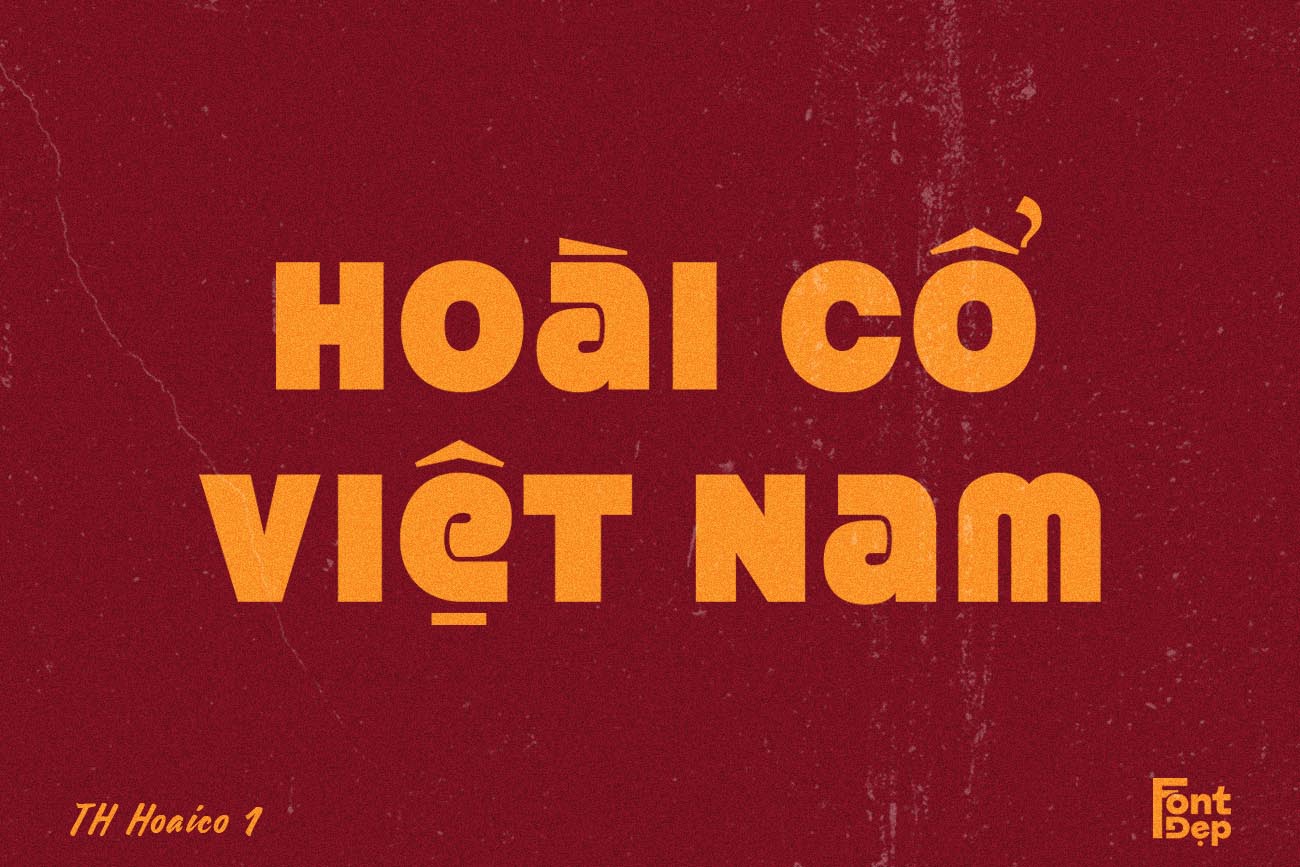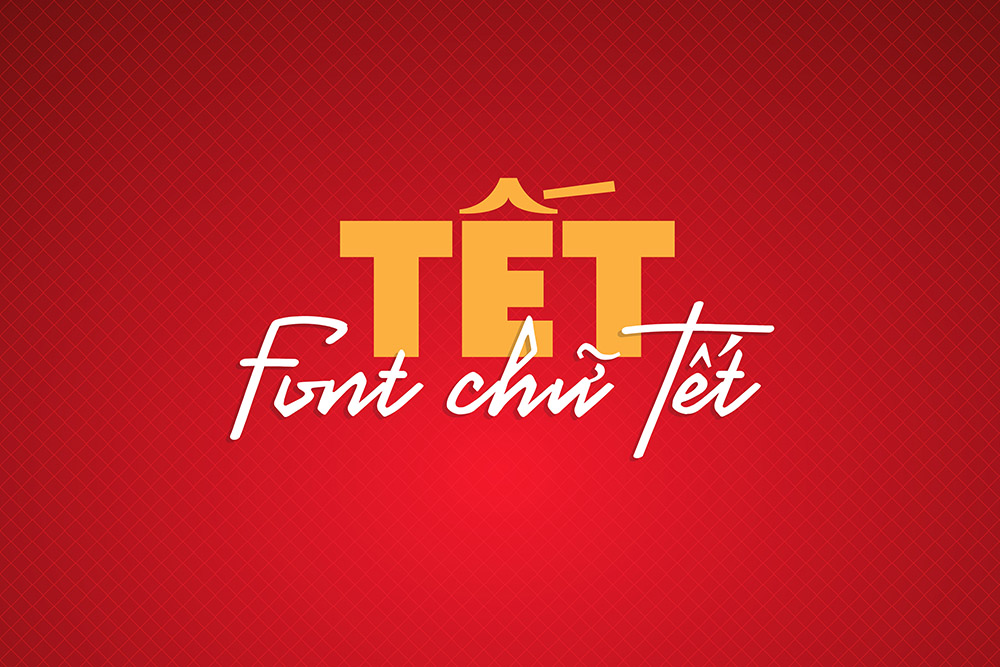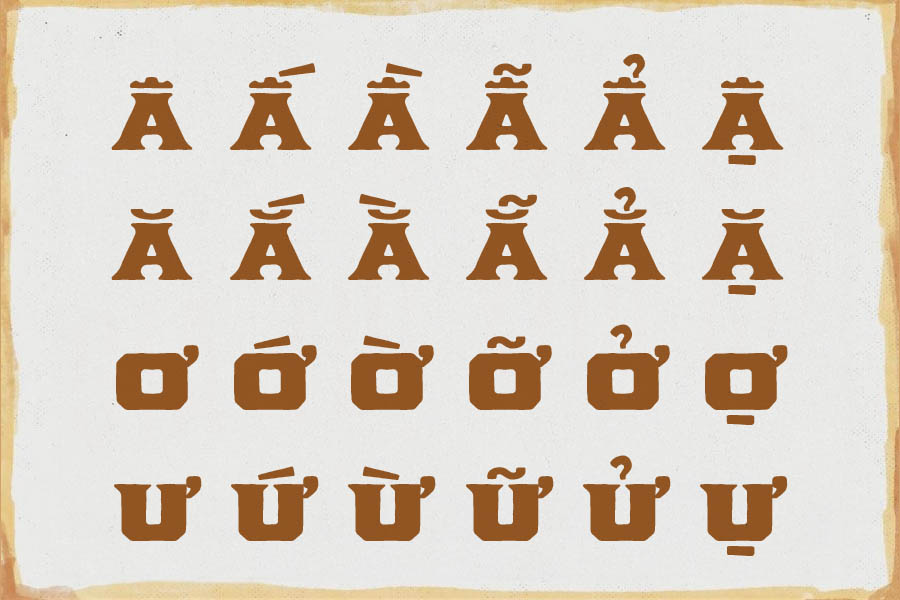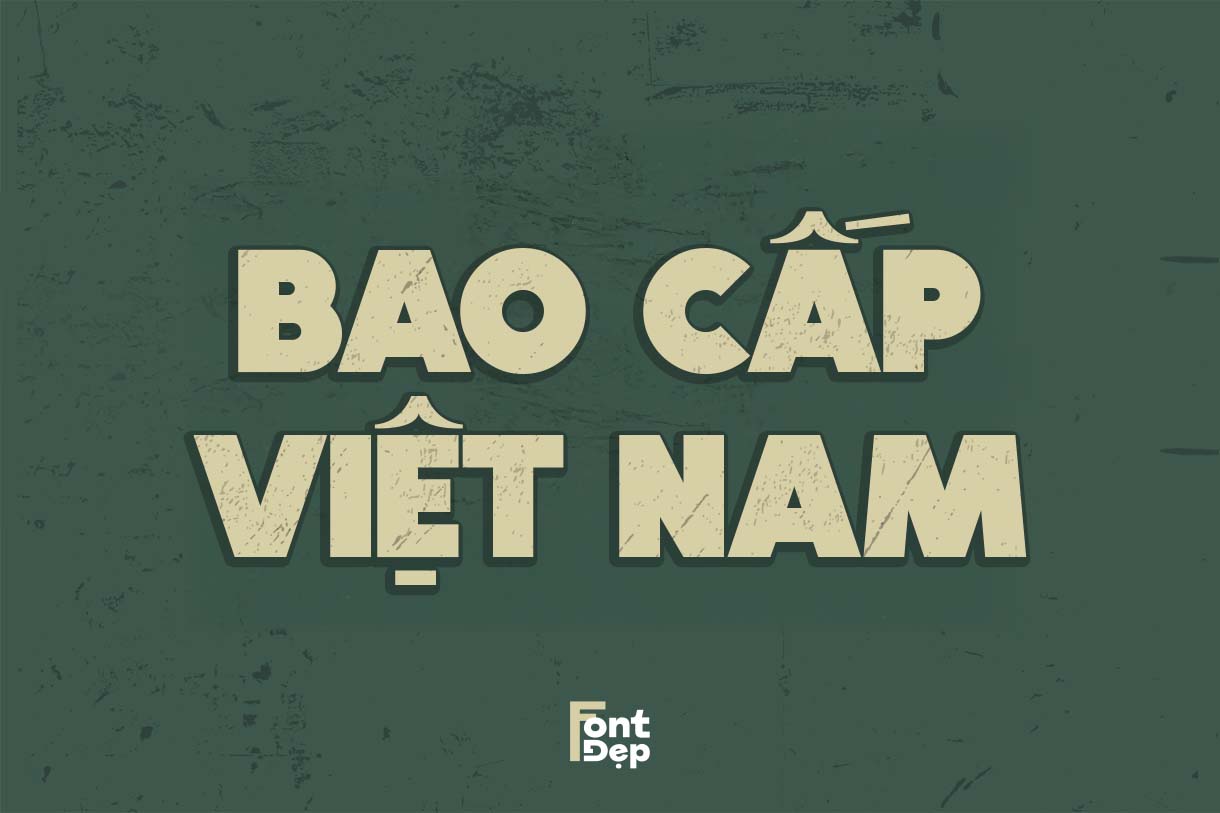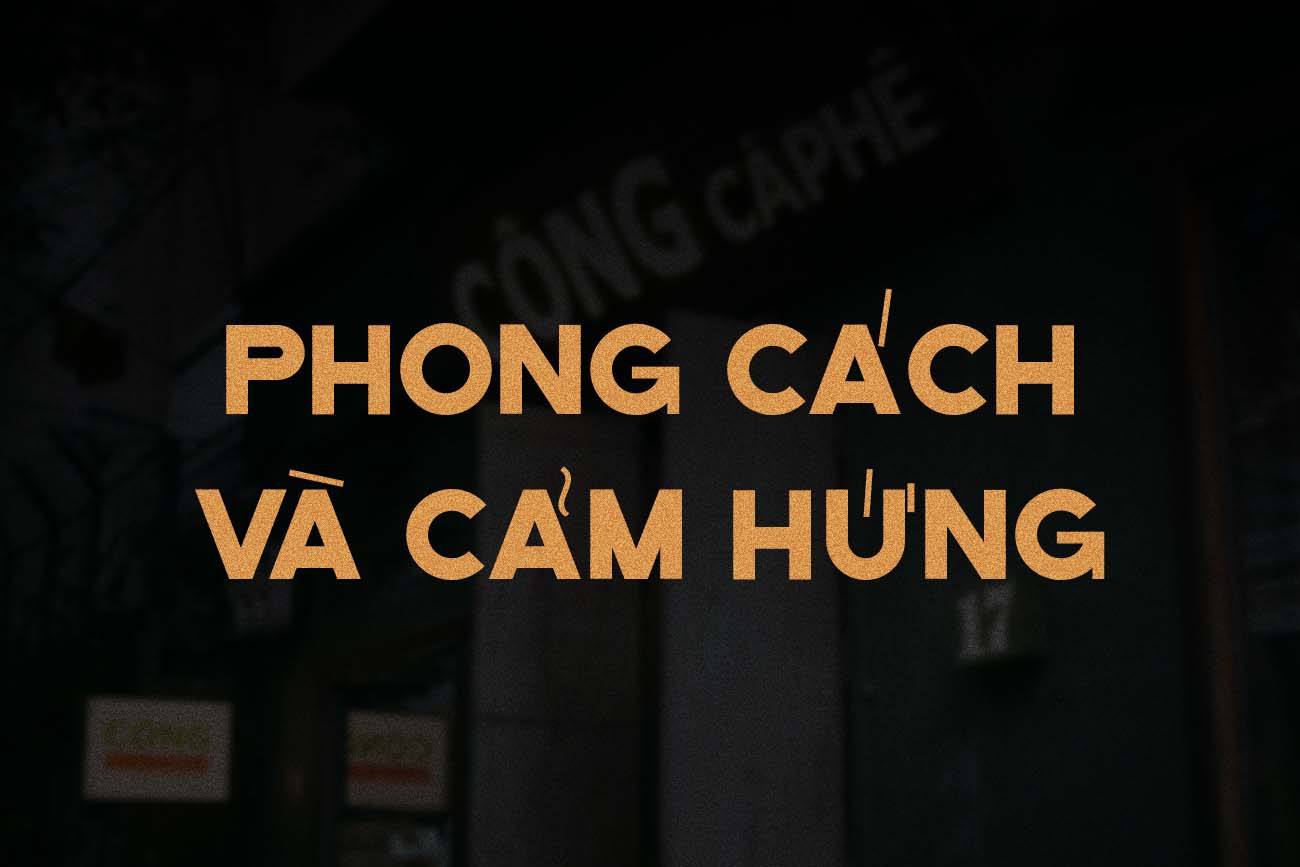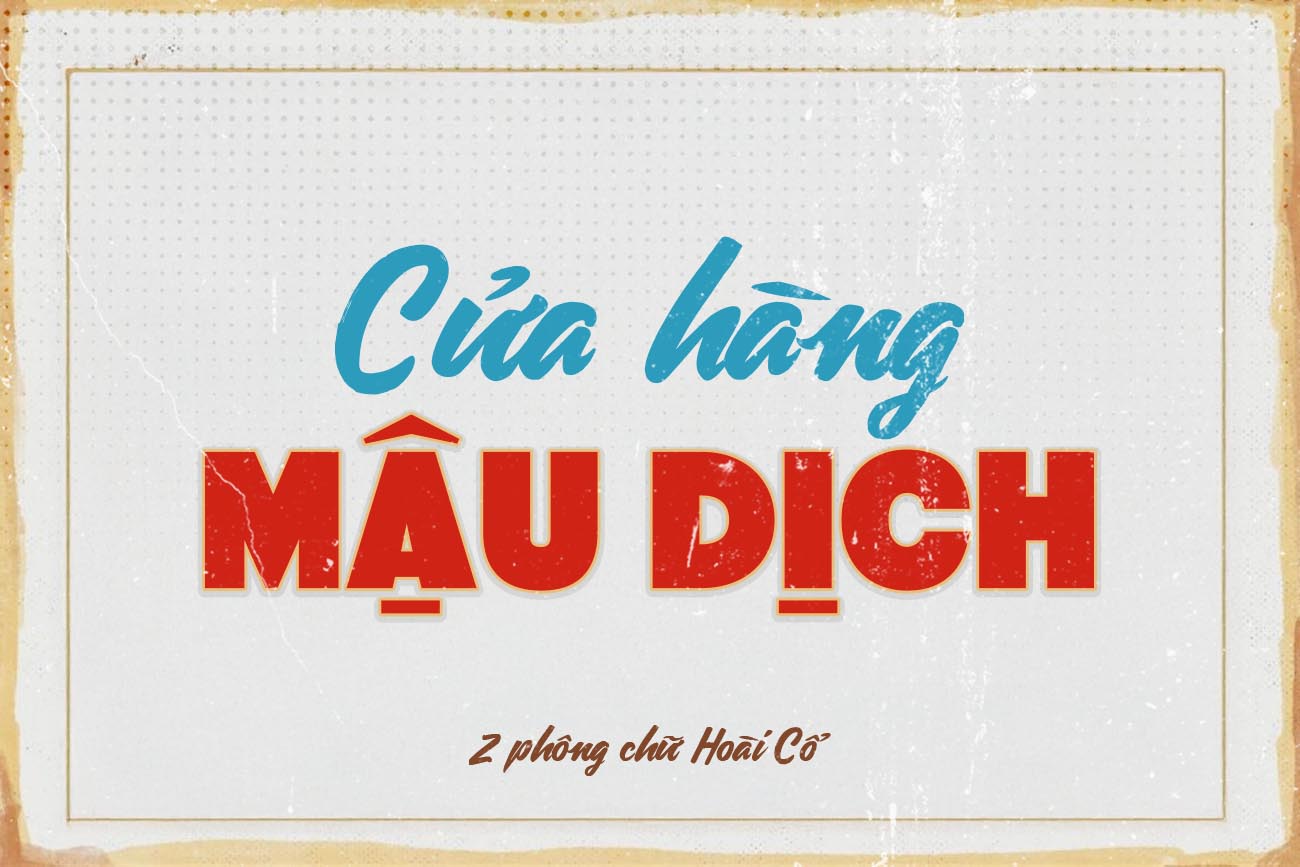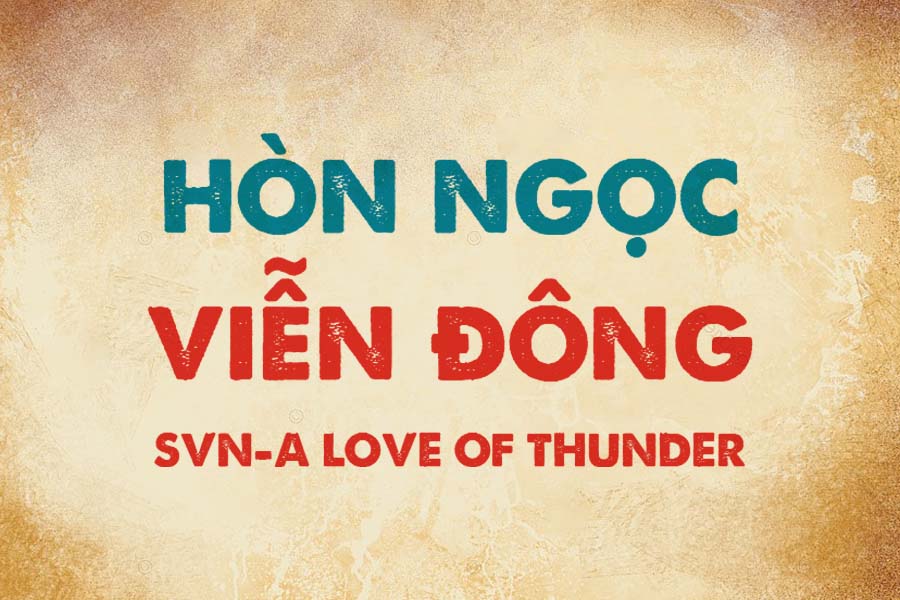
Bộ sưu tập Font Chữ Thời Bao Cấp Việt Hóa tái hiện trọn vẹn tinh thần hoài cổ Việt Nam, kết hợp di sản xưa với thẩm mỹ thiết kế hiện đại đầy cảm xúc.
Tải ngay Bộ Sưu Tập Font Chữ Thời Bao Cấp Việt Hóa – từ phong cách mộc mạc, thủ công đến nét viết tay bay bổng, tái hiện trọn vẹn cảm xúc hoài niệm và sâu lắng của những năm tháng cũ.
Bộ sưu tập hoàn hảo giúp bạn tạo nên những ấn phẩm thiết kế đậm chất xưa, giàu cảm xúc và chuyên nghiệp.
Font chữ thời Bao Cấp (khoảng thập niên 1970–1980) không chỉ là một kiểu chữ, mà là dấu ấn văn hóa – nhân chứng cho một giai đoạn đặc biệt của Việt Nam.
Việc sử dụng những font này giúp truyền tải sự chân thật, mộc mạc, thủ công – điều mà các font hiện đại khó có thể mô phỏng được.
Trong bài viết này, Fontdep.vn sẽ gợi ý những font chữ Bao Cấp / Hoài Cổ Việt Hóa chất lượng cao nhất, giúp bạn dễ dàng chọn được kiểu chữ hoàn hảo để hồi sinh nét đẹp hoài niệm trong mọi dự án thiết kế.
Font Chữ Thời Bao Cấp: Dấu Ấn Typography Của Một Giai Đoạn Lịch Sử
Font chữ thời Bao Cấp là gì?
Định nghĩa
Font Chữ Thời Bao Cấp là thuật ngữ chỉ các kiểu chữ được sử dụng rộng rãi trong các ấn phẩm, bảng hiệu, áp phích tuyên truyền, và bao bì sản phẩm trong thời kỳ kinh tế kế hoạch hóa tập trung (thời kỳ Bao cấp) tại Việt Nam.
Bối cảnh thiếu thốn vật liệu và công nghệ in ấn hiện đại đã buộc người thợ phải tự tay thiết kế và vẽ chữ, tạo nên một phong cách typography độc đáo: tự phát, thủ công, đầy ngẫu hứng và chân thật. Phong cách này khác biệt hoàn toàn với sự chuẩn mực của font kỹ thuật số ngày nay.
Đặc Điểm Nhận Dạng (Hình thái) Của Font Bao Cấp:
Các font mô phỏng phong cách Bao cấp thường mang những đặc trưng hình thái sau:
• Tính Thủ Công & Đơn Giản: Font thường là dạng Sans Serif hoặc Script thô sơ, mô phỏng nét cọ, nét sơn, thiếu sự đối xứng, hoàn hảo của font hiện đại.
• Tâm Lý Thiết Kế: Màu sắc, bố cục thường gắn với sự lạc quan, tuyên truyền và sự chắt chiu (tận dụng không gian).
• Yếu Tố Việt Hóa Quyết Định: Yếu tố quyết định là việc xử lý các dấu tiếng Việt (thanh sắc, huyền, hỏi, ngã, nặng) phải giữ được nét thủ công, không quá cứng nhắc, tránh phá vỡ sự liền mạch của chữ.
Ứng Dụng Nổi Bật Của Font Chữ Bao Cấp Trong Thiết Kế Hiện Đại
Font chữ thời Bao cấp có tính ứng dụng rất đa dạng, đặc biệt quan trọng trong các ấn phẩm cần truyền tải chiều sâu hoài niệm, sự mộc mạc thủ công và chất xưa độc đáo:
• Thương hiệu Ẩm thực Truyền thống: Sử dụng font Mộc mạc & Bảng hiệu cho bao bì cà phê rang xay thủ công, đặc sản địa phương, hoặc logo quán ăn/thương hiệu gợi nhớ hương vị xưa cũ.
• Thiết kế Hoài cổ/Retro Việt Nam: Áp dụng font Retro & Ấm áp cho poster phim, trang trí nội thất quán cà phê, hoặc các ấn phẩm tái hiện không khí thập niên 70-90.
• Ấn phẩm Cá nhân hóa/Nghệ thuật: Dùng font Viết tay & Bay bổng cho thiệp mời sự kiện cá nhân, chữ ký thương hiệu thời trang thủ công, hoặc tiêu đề blog mang tính kể chuyện.
• Sự kiện Văn hóa/Cộng đồng: Sử dụng font Mộc mạc/Script để thiết kế bảng chào mừng hoặc banner cho các lễ hội, sự kiện văn hóa cộng đồng cần sự chân thật và gần gũi.
Danh Sách 10 Font Chữ Thời Bao Cấp/Hoài Cổ Việt Hóa Tuyệt Đẹp
Fontdep.vn đã tuyển chọn 10 font chữ thời bao cấp tiêu biểu, được chọn lọc và Việt Hóa hoàn chỉnh, giúp nhà thiết kế dễ dàng áp dụng.
1. Font Sans-serif DT Phudu Việt Hóa – Mộc mạc, đồng quê
Font DT Phudu là font chữ cổ điển mang phong cách đồng quê Việt Nam, với những nét vẽ mộc mạc và hơi thô, mô phỏng chữ vẽ tay trên biển hiệu vùng quê. Font này đặc biệt phù hợp cho các dự án về văn hóa dân gian, nông nghiệp, làng nghề truyền thống, Tết Nguyên Đán.
Font chữ phong cách hoài cổ của Việt Nam xưa DT Phudu
2. Font Sans-serif TH Hoaico 20 Việt Hóa – Sài Gòn xưa
TH Hoaico 20 là font chữ sans-serif đậm, chắc khỏe, góc cạnh, gợi nhớ về hình ảnh “Hòn Ngọc Viễn Đông” – một Sài Gòn xưa hoa lệ. Font này đặc biệt phù hợp cho poster, bảng hiệu, bao bì mang hơi hướng retro, vintage.
Font chữ Sài Gòn xưa – TH Hoaico 20 Việt Hóa
3. Font Sài Gòn xưa Việt Hóa - Cho thiết kế bảng hiệu
Là sự kết hợp giữa TH Hoaico 17 và TH Hoaico 63 tạo nên một cặp đôi hoàn hảo: một bên uyển chuyển, gợi cảm xúc, một bên mạnh mẽ, gây ấn tượng thị giác. Khi phối hợp trong cùng một thiết kế, chúng giúp người xem ngay lập tức liên tưởng đến hình ảnh font chữ Việt Nam xưa, vừa quen thuộc vừa hoài niệm. Đây là lý do bộ font này rất phù hợp để làm poster triển lãm, thiết kế vintage, banner sự kiện hay bao bì gợi nhớ thời kỳ bao cấp.
2 font chữ Sài Gòn xưa Việt hóa cho thiết kế bảng hiệu
4. Font Display SVN A Love Of Thunder Việt Hóa – Áp phích tuyên truyền
SVN-A Love of Thunder là font chữ display không chân, thiết kế theo phong cách áp phích tuyên truyền thời bao cấp với những nét chữ in đậm, rắn rỏi và hiệu ứng rách nhẹ như in trên giấy cũ. Rất lý tưởng cho tiêu đề lớn hoặc slogan.
[Tải Miễn Phí] SVN A Love of Thunder – Font Hoài Cổ, Đậm Chất Xưa Cũ & Việt Hóa Chuẩn
5. Font Retro TH Hoaico 3 Việt Hóa – Vuông vức, dứt khoát
TH Hoaico 3 sở hữu hình dáng chữ vuông vức, cấu trúc đơn giản nhưng dứt khoát. Font giữ sự cân bằng tốt giữa cổ điển và hiện đại, phù hợp với không gian mang tính cộng đồng hoặc văn hóa bản địa.
6. Font TH Hoaico 2 Việt Hóa – Mộc mạc & Hoài niệm
Font TH Hoaico 2 tái hiện đậm nét phong cách hình ảnh thời kỳ bao cấp, mang đậm chất công nghiệp cổ điển. Các cạnh chữ không hoàn hảo, có phần loang hoặc nứt nhẹ, mang đến cảm giác gần gũi, chân thực.
TH Hoaico 2 – Font Chữ Việt Hóa Mang Hơi Thở Thời Bao Cấp, Mộc Mạc và Hoài Niệm
7. Font Sans-serif TH Colombo Sans Việt Hóa – Hành chính, báo chí
Font Sans-serif TH Colombo Sans thuộc nhóm sans-serif, nhưng lại gợi cảm giác rất cổ điển, giống như những tiêu đề báo chí, áp phích tuyên truyền hay các tài liệu hành chính của những năm 1975–1990.
• Tác giả gốc: Đang update
8. Font Xưa cũ TH Delaqrus Việt Hóa – Phong cách hoài cổ
Font TH Delaqrus Việt Hóa thuộc nhóm Sans - serif mang phong cách xưa cũ, hoài cổ rõ rệt. Thường được sử dụng để tái hiện các ấn phẩm, tài liệu mang dấu ấn thời gian.
Font chữ phong cách xưa cũ TH Delaqrus Việt Hóa
9. Bộ font chữ hoài cổ cho ngày Tết cổ truyền Việt Nam
Bộ font chữ này là sự kết hợp hoàn hảo giữa nét truyền thống, trang trọngsự mềm mại, bay bổng của không khí Tết Nguyên Đán, giúp các ấn phẩm thiết kế trở nên nổi bật và giàu cảm xúc.
10. Font Retro Bao Cấp TH HC Calvous – Mộc mạc, đơn giản
TH HC Calvous là font chữ mang phong cách hoài cổ 'thời bao cấp', với nét chữ mộc mạc, đơn giản, gợi cảm giác chân thật về quá khứ Việt Nam thời kỳ 1970-1990.
• Tác giả gốc: Hendry Juanda
• Việt hóa bởi: Font TH
• Tải về: TH HC Calvous
Font chữ tiếng Việt phong cách hoài cổ của thời bao cấp TH - HC Calvous
Hướng Dẫn Cài Đặt Font Việt Hóa Nhanh Chóng
Trên Windows:
1. Tải file font (.ttf hoặc .otf).
2. Nhấp chuột phải → chọn Install / Cài đặt.
3. Mở Photoshop, Illustrator hoặc Canva để sử dụng ngay.
Trên macOS:
1. Mở ứng dụng Font Book.
2. Kéo thả file font vào cửa sổ.
3. Nhấn Install Font và kiểm tra các ký tự có dấu (ư, ă, ê, đ…) để đảm bảo hiển thị đúng.
Kết Luận
Bộ sưu tập Font Chữ Thời Bao Cấp Việt Hóa là một tài sản typography quý giá, đóng vai trò như một cầu nối giữa quá khứ và hiện tại. Chúng không chỉ là công cụ thiết kế mà còn là người kể chuyện về một giai đoạn lịch sử đầy ý nghĩa, mang lại sự mộc mạc, chân thật và cảm xúc hoài niệm sâu sắc.
Việc nắm vững bộ sưu tập font Việt hóa tinh hoa này và áp dụng chúng theo các nguyên tắc phối hợp chuyên nghiệp sẽ giúp bạn nâng tầm dự án thiết kế, tạo ra những ấn phẩm không chỉ đẹp mắt mà còn giàu ý nghĩa văn hóa và cảm xúc.